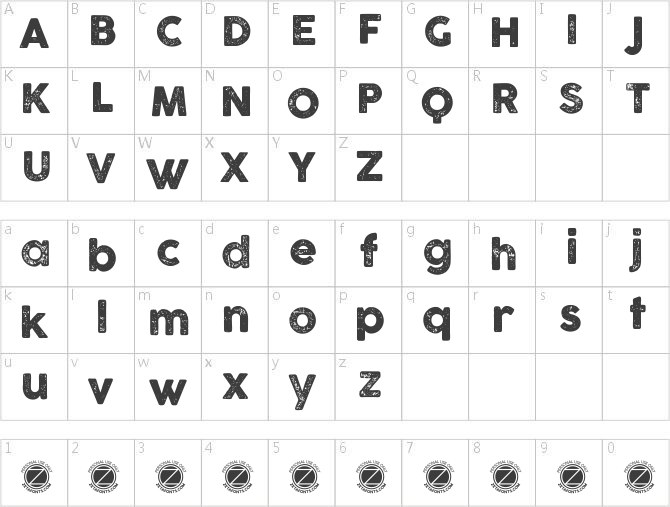
COCOGOOSE LETTERPRESS
COCOGOOSE LETTERPRESS介紹
COCOGOOSE LETTERPRESS字體字庫是一款讓人賞心悅目、百看不厭的英文字體,適合各類廣告和產(chǎn)品包裝設(shè)計應(yīng)用,字體大小0.71MB,格式為ttf字體,上傳用戶是蕪耆蕪,作者/版權(quán)方為未知